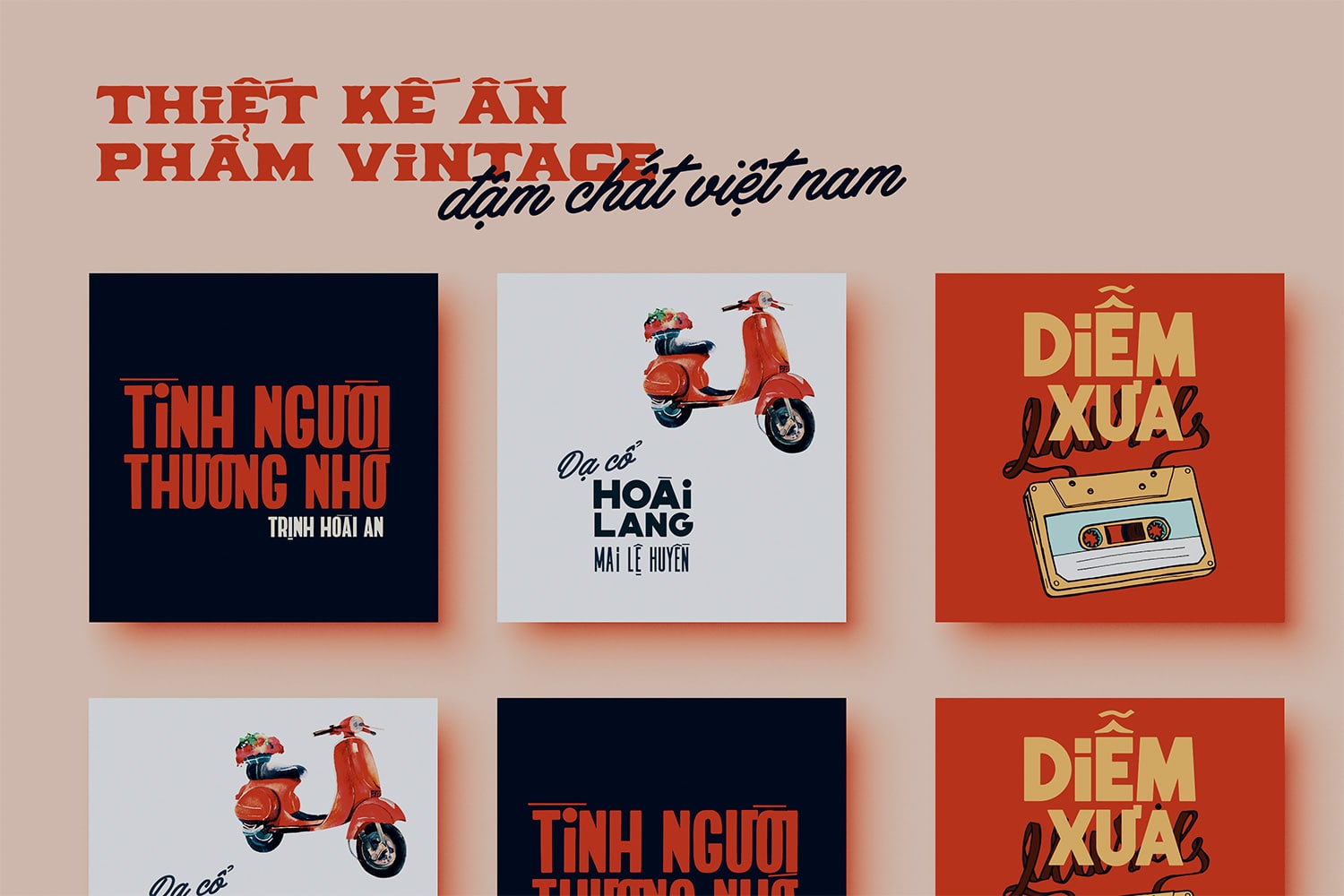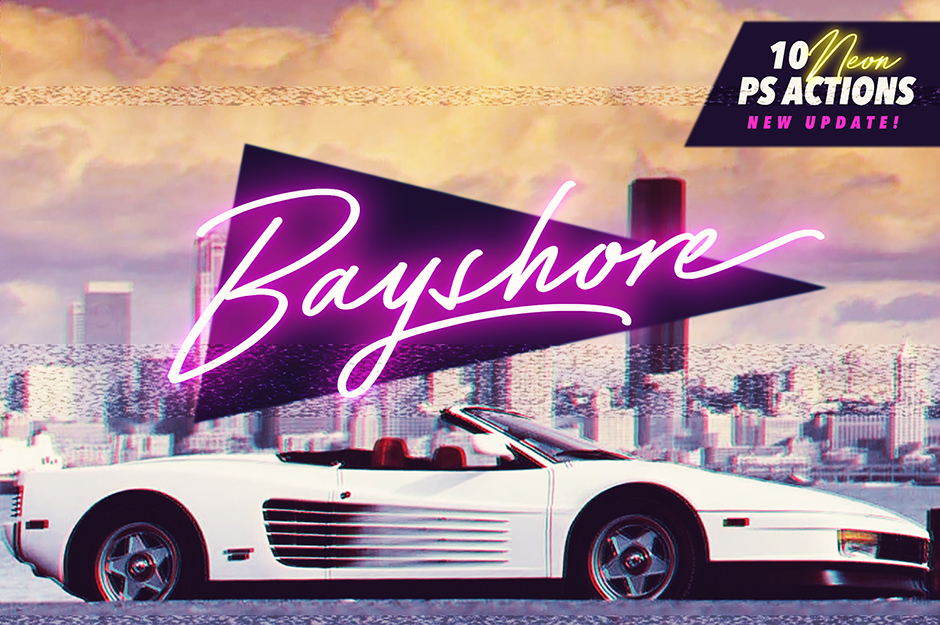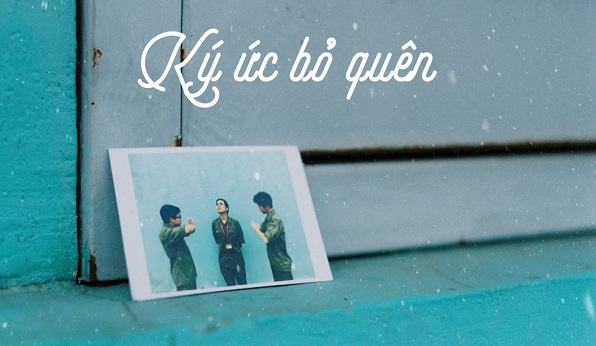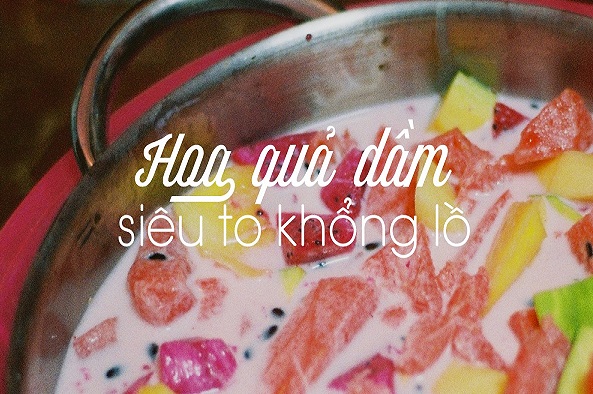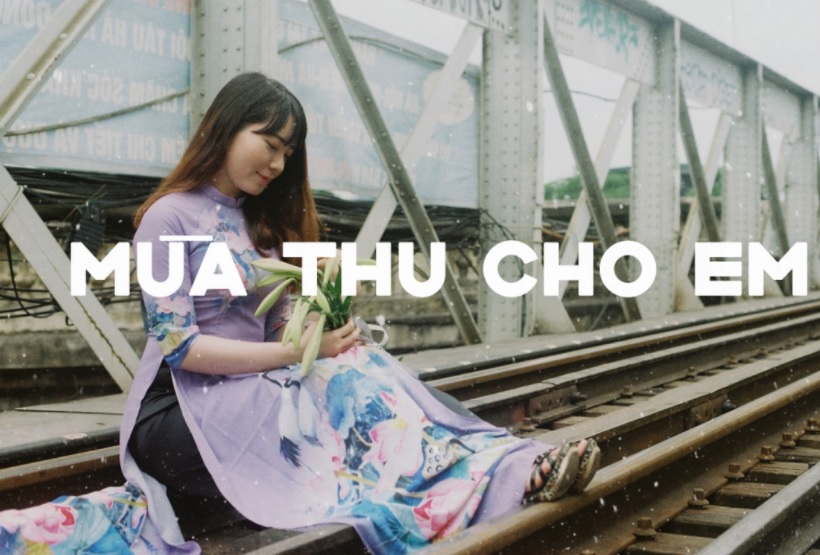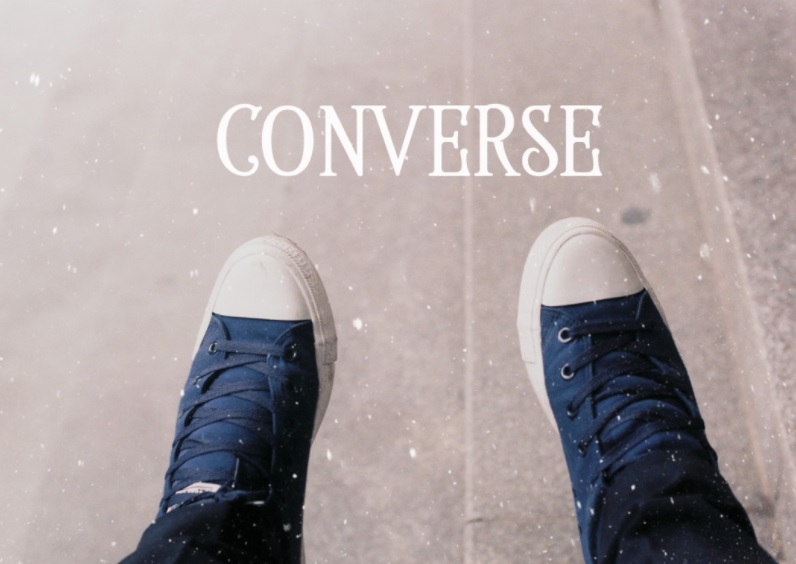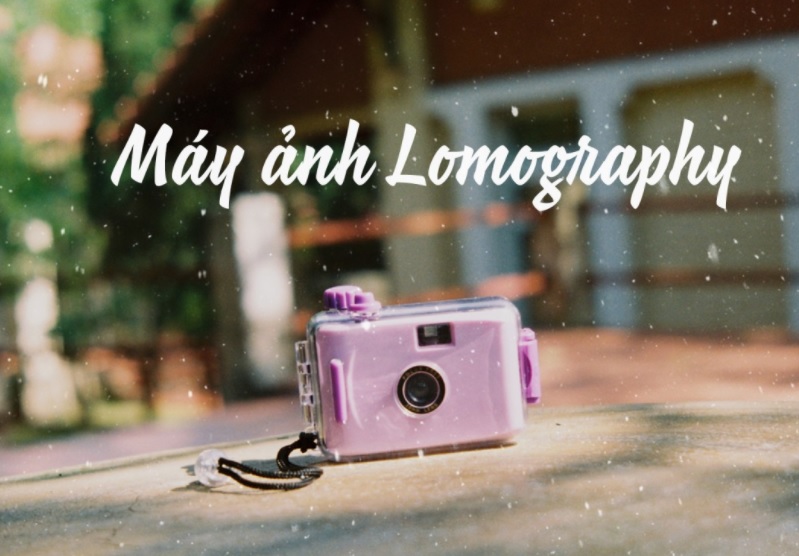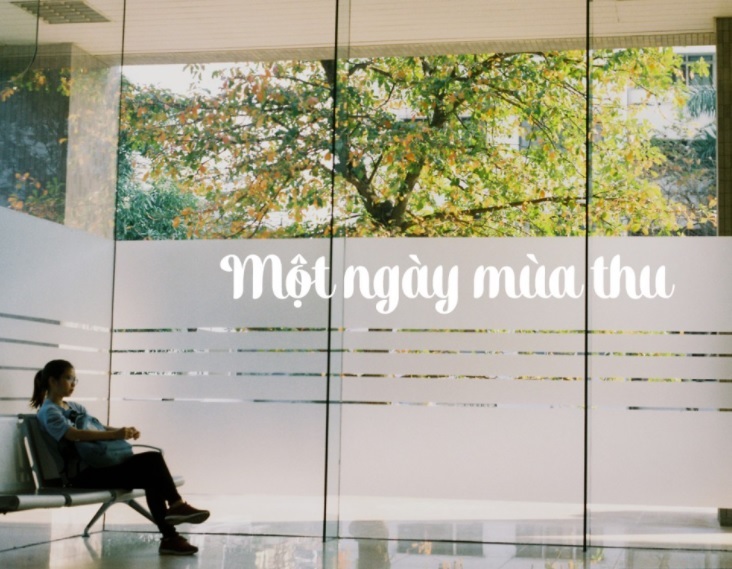
Vintage là gì? 11 font chữ Vintage Việt hóa đẹp nhất
Bạn là một người am hiểu thiết kế hoặc có niềm đam mê học thiết kế thì không còn xa lạ với chữ Vintage việt hóa được rất nhiều người yêu thích. Từ những nét đẹp trong quá khứ, nó được làm mới vào cuộc sống hiện đại với những nét hoài cổ, sang trọng. Vintage là gì? Các mẫu font chữ vintage Việt hóa đẹp nhất. Cùng tìm hiểu ngay.
Font chữ Vintage là gì?
Vintage là mang nghĩa là cổ- cũ, được sử dụng trong nhiều lĩnh vực như thời trang, nội thất, nhiếp ảnh hay đồ họa. Font chữ Vintage là một kiểu chữ của sự hoài niệm, của dấu ấn theo thời gian.
11 Font chữ vintage Việt hóa
Phông chữ cổ điển có khả năng vận chuyển công việc của bạn và mang lại cho nó cảm giác hoài cổ và vượt thời gian mà không một phong cách nào khác có thể thực sự mô phỏng được.
Font Classique Saigon
Font chữ Vintage đầu tiên mà UNICA muốn giới thiệu cho các bạn mang đậm chất Sài Gòn, gọn gàng của những thập kỷ trước. Classique Saigon là đứa con được tạo bởi Mạnh Nguyễn, một người yêu thích thiết kế, yêu thích nét cổ điển từ những tấm bảng hiệu viết tay.
Tuy nhiên mẫu Classique Saigon không chỉ được dựng lại theo y mẫu của thời kỳ trước mà nó còn được sáng tạo rất công phu, tỉ mỉ, hiện đại. Các designer thường sử dụng mẫu này trong các thiết kế mang tính retro hoặc các banner, backdrop, brochure, hình ảnh fanpage.
Font Wallington
Đây là một phông chữ trang trí với những đường cong cổ điển và rất thanh lịch, nó được lấy cảm hứng từ cấu trúc tự nhiên với đường cong mềm mại của văn hóa Anh cổ. Có thể nhận thấy Font chữ này rất đẹp, dễ sử dụng và cực kỳ dễ đọc. Được bắt nguồn từ cảm hứng từ những tác phẩm mang tính nghệ thuật đương đại tại thế kỷ 19. Font chữ Wallington được cho ra mắt với những đường nét tinh tế mang đậm tính chất nghệ thuật.
Font Authentica Regular
Đây font chữ tiếp theo trong nhóm các Font Vintage Việt hóa mà chúng tôi muốn bật mí đến các bạn. Nó là font script hiện đại nhưng rất giản dị, thanh lịch và nhiều lợi ích. Cụ thể, ưu điểm đầu tiên là dễ dàng sử dụng trong bất kỳ tác phẩm nghệ thuật nào từ hiện đại cho đến giản dị, cổ điển, retro, trang trọng, sáng tạo đến tối giản. Nó còn chứa thêm những tính năng rất ưu Việt như Open Type để bạn thoải mái sáng tạo. Đặc biệt hơn, bạn có thể trộn và kết hợp các ký tự thay thế để tạo ra một thông điệp đặc biệt cho thiết kế.
Font Shintia Script
Shintia Script là kiểu chữ Script rất dễ đọc, với nét chữ đậm, sắc thái cổ điển nhưng vẫn toát lên được sự nhí nhảnh, vui nhộn và hồn nhiên. Font chữ này được sử dụng cho rất nhiều mục đích như làm poster,  áo, logo
Font L' Hanoienne
Sau sự thành công của font chữ Sài Gòn, nhà thiết kế Mạnh Nguyễn đã cho ra mắt một bộ font chữ L' Hanoienne nổi tiếng về Hà Nội. Để bày tỏ tình yêu nước nồng nàn và tình cảm thiêng liêng ngàn năm văn hiến. Anh đã cho ra bộ font chữ đẹp mắt này.
Mặc dù có khá nhiều nét tương đồng trong thiết kế của Classique Saigon. Nhưng L' Hanoienne vẫn mang đến những trải nghiệm thú vị cho người đọc. Dưới sự kết hợp tính tế, cấu trúc nhẹ nhàng rất phù hợp vẻ đẹp người phụ nữ Việt Nam hiền dịu, nhẹ nhàng trong thế kỷ 20.
Font Coco FY
Là một font chữ thuộc dòng script vintage, font chữ này thường xuyên được xuất hiện trên những biển hiệu quảng cáo tại cả cửa hàng ngoài phố hoặc những tấm banner treo tường. Với sự tương phản cao và dạng chữ đường nét được thiết kế khá rõ ràng, Coco Fy hứa hẹn sẽ đem tới cho bạn một phong cách retro cổ kính trong các thiết kế của bạn.
Bertrand Reguron và Gia Tran là nhà người đồng sáng lập lên font chữ Coco fy trên fontyou.com
Font Selfie Regular
Font chữ vintage Việt hóa tiếp theo mà bạn cần lưu về đó là Selfie Regular. Kiểu font này dựa vào một font sans Serif dựa trên những biểu hiện vintage viết tay ở Buenos Aires. Ưu điểm của nét chữ này là thanh mảnh, mang phong cách màu Nam Mỹ.
Font Alek
Được thiết kế bao gồm 2 định dạng ( Regular và Bold ) nằm trong cùng một bộ ornaments. Font chữ thiết kế mang một sắc thái quan trọng, vui tươi nhưng không kém phần lịch lãm và sang trọng. Việc kết hợp font chữ Alek cùng với ornaments để kiểu chữ được trở nên hoàn hảo nhé.
Font Rumble Brave
Bộ sưu tập phông chữ tuyệt vời Rumble Brave Vintage đã có ở đây! Phông chữ này mang đến cho bạn sự sang trọng, thanh lịch và phong cách tất cả trong một.